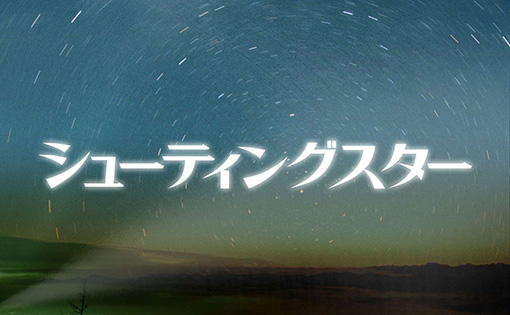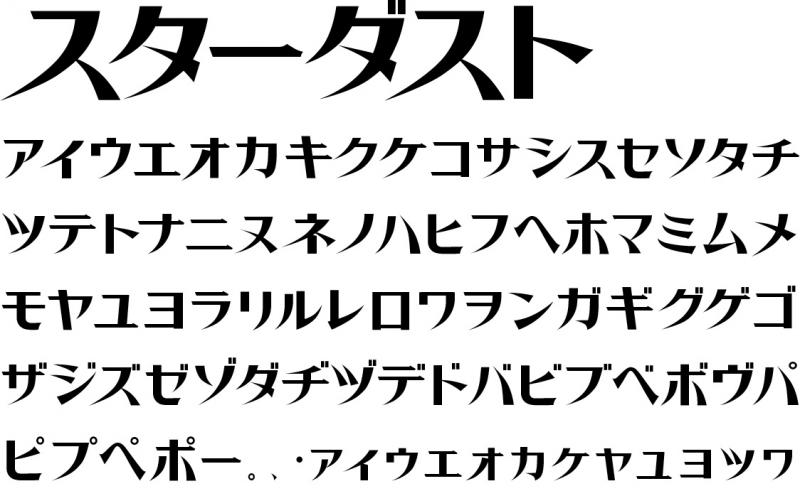
スターダスト|Chiba Design|和文・欧文・デザイン書体のダウンロード販売|フォントファクトリー
商用利用可能なオリジナルフォントです。Open Type・ 2バイト・カタカナのみ。アウトライン化可能。ラインを細くし、ふところを深くとったフォントです。エレガントな中にも力強さを持っています。ロゴの作成などに便利です。
スターダスト